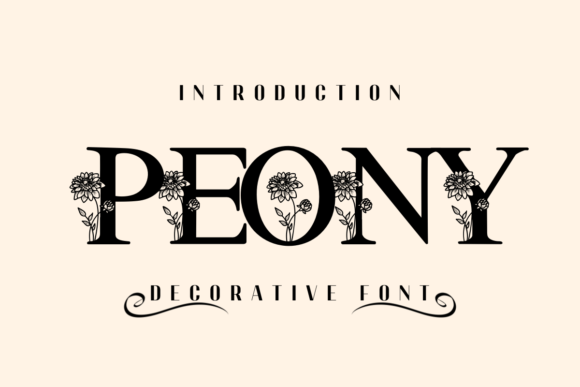
Peony Font
Peony Font – خط بيوتي الأنيق والمميز
أضف لمسة من الأناقة والتميز إلى تصاميمك مع Peony Font، الخط المثالي للمبدعين والمصممين الذين يبحثون عن أسلوب راقٍ وفريد. يتميز هذا الخط بحروفه الانسيابية وتصميمه الأنيق، مما يجعله الخيار الأمثل لاستخدامه في الشعارات، والتصميمات الدعائية، والدعوات، والعلامات التجارية، والمطبوعات الفاخرة.
✔️ تصميم أنيق وسلس يناسب مختلف الاستخدامات
✔️ مثالي للعلامات التجارية، الدعوات، العناوين، والتصاميم الرقمية